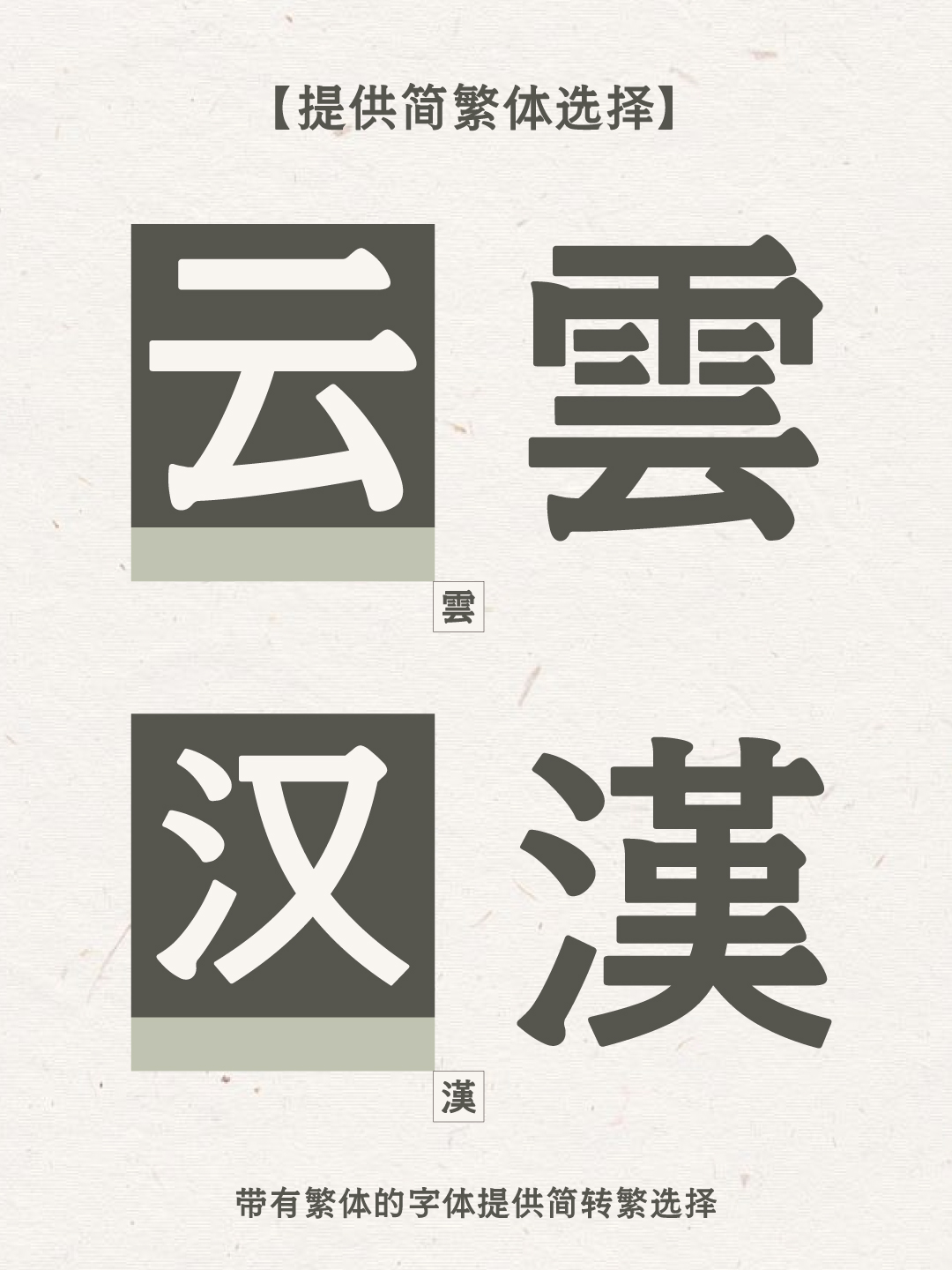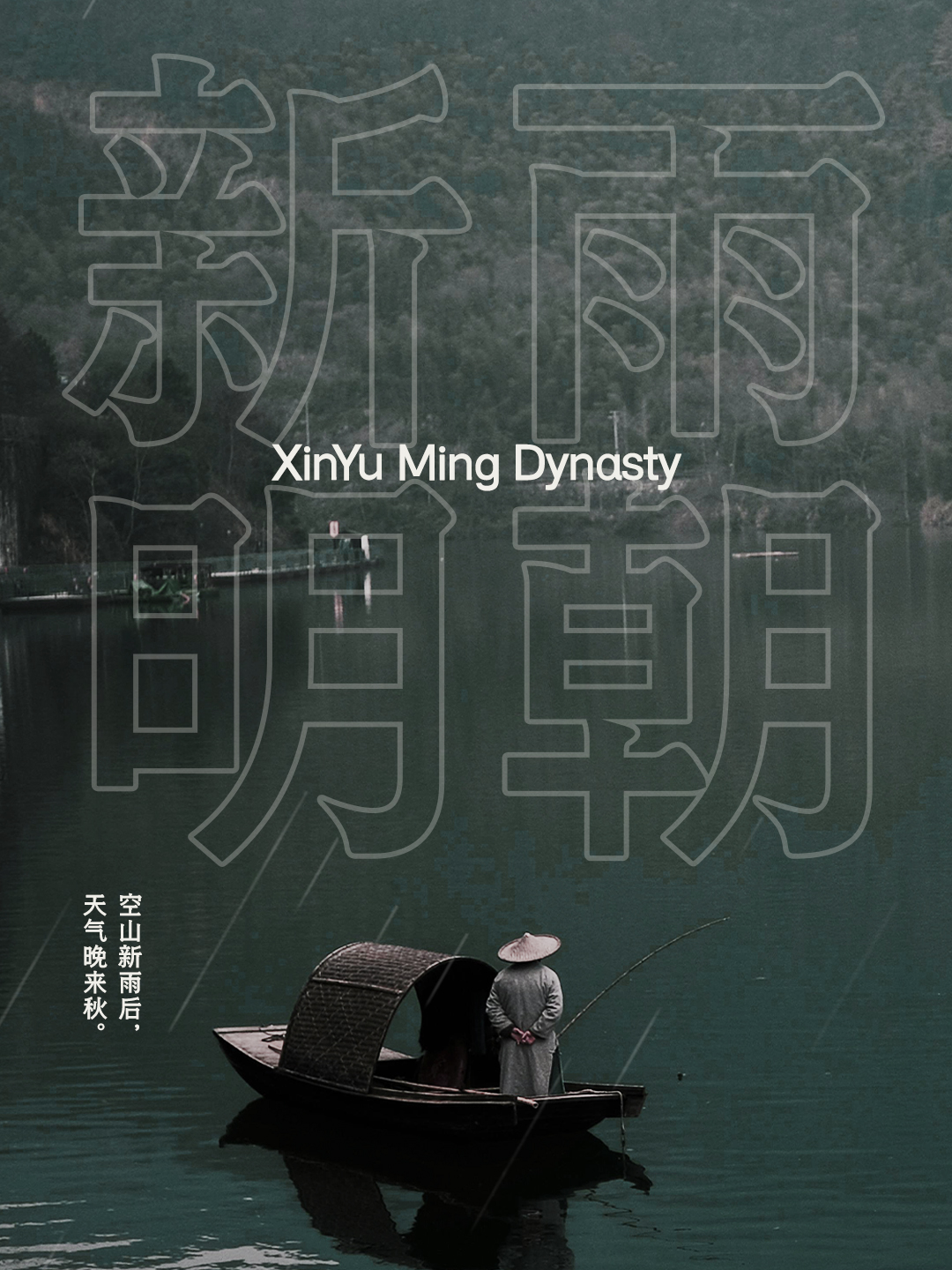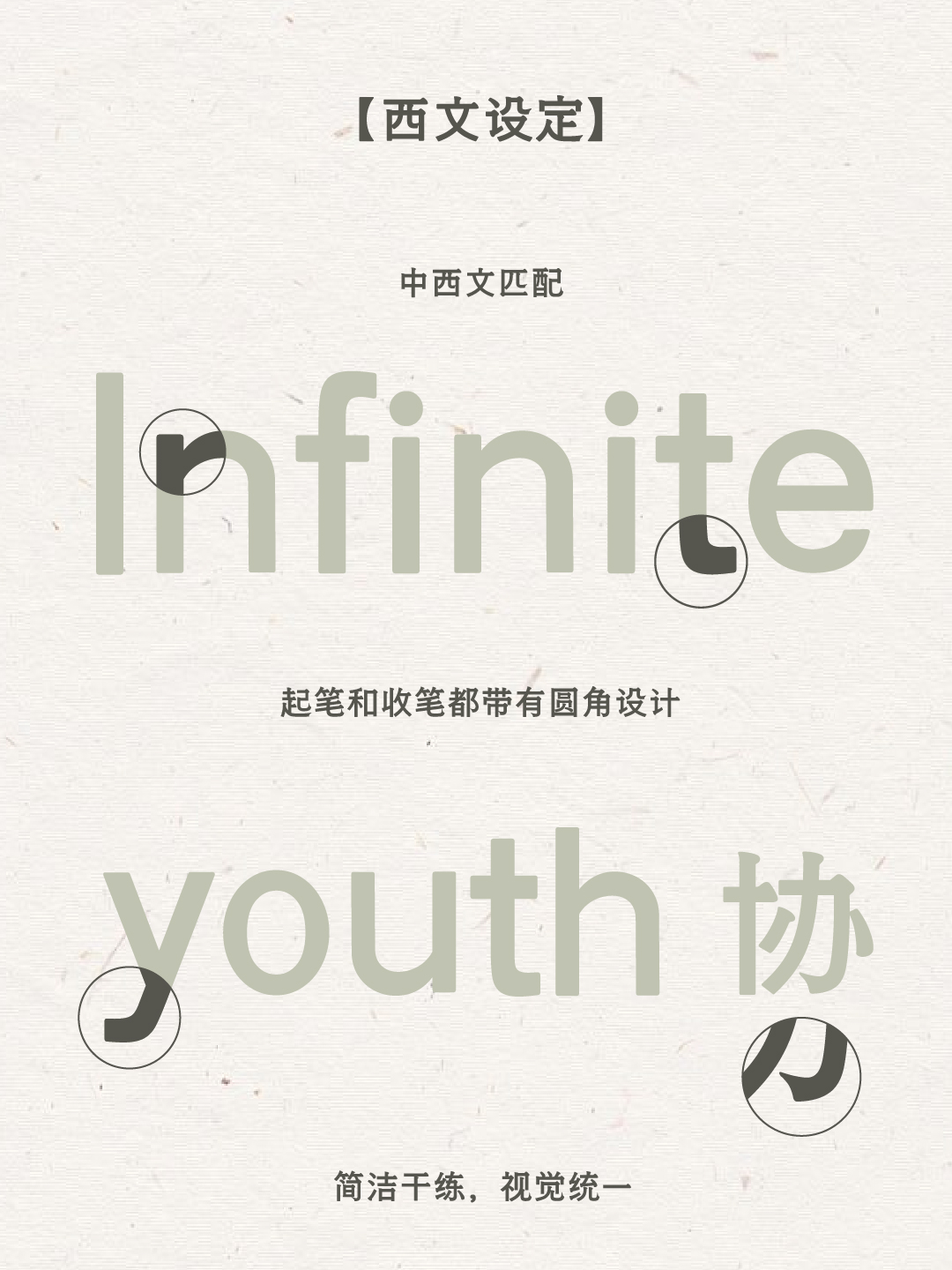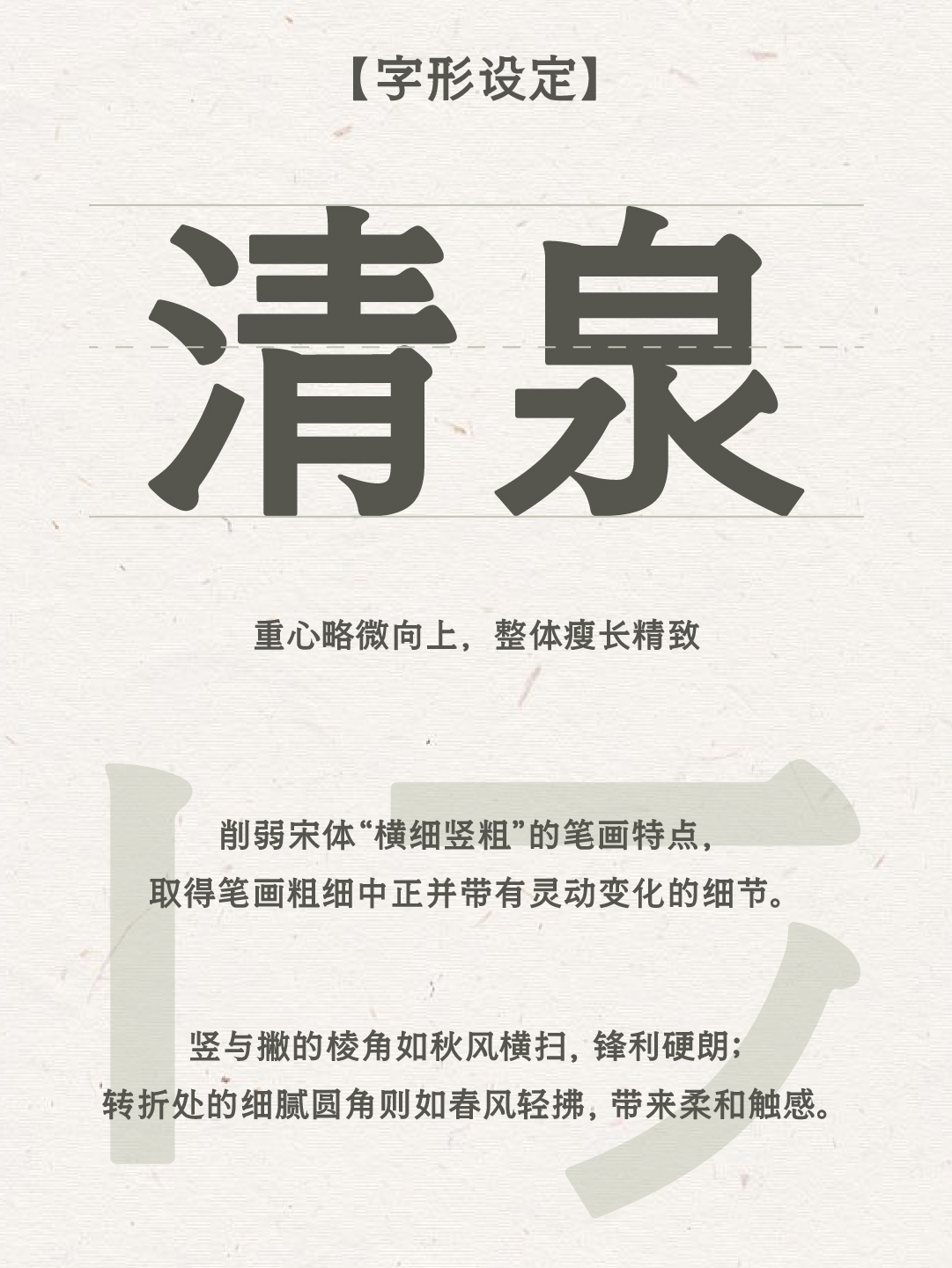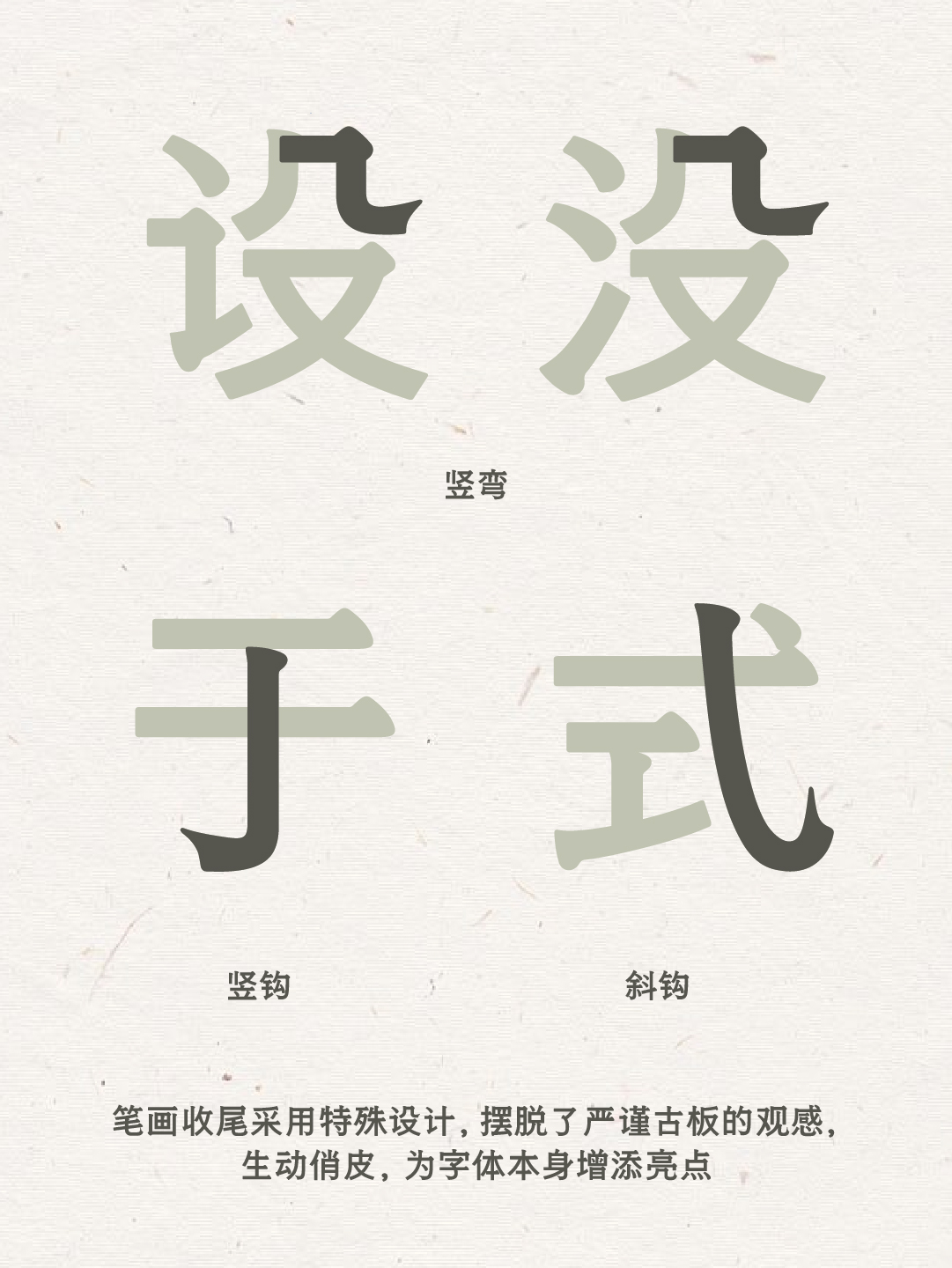
【字体创意溯源】
“空山新雨后,天气晚来秋”,王维笔下《山居秋暝》里的“新雨”意境,宛如一幅清新隽永的画卷,在眼前徐徐展开。雨过天晴,世间万物仿佛被赋予了新的生命,焕发出勃勃生机,而雨本身,也象征着事物在时光流转中的蜕变与新生。这套「新雨明朝体」字体,恰似从这诗意的意境中汲取灵感,在传承宋体端正、优雅风姿的同时,巧妙融入黑体的锐利与力量感,二者相互交融、平衡共进,这正是「也字工厂」制字理念的生动诠释——温柔中蕴含锋芒,于传统里拥抱创新,书写着字体设计的独特篇章。
【字体独特魅力】
「新雨明朝体」是「也字工厂」专业团队耗时一年精心雕琢的精品字体,它实现了简繁扩展,能够满足不同场景的使用需求。
宋体与黑体的完美融合:它既保留了宋体的端庄典雅,又融入了黑体的锐利刚劲,达成古典与现代的精妙平衡。相较于传统宋体,它多了一份硬朗与果敢;相较于黑体,又增添了几分优雅与温婉,在字体的世界里独树一帜。
笔画刚柔并济的艺术:仔细观察其笔画,竖与撇的棱角犹如秋日里飘落的树叶,边缘锋利,展现出一种坚韧不拔的个性;而转折处的细腻圆角处理,又仿佛春风轻拂脸颊,给人以温柔细腻的触感,刚与柔在这里达到了和谐的统一。
灵动细节的巧妙点缀:在“钩”的细节处理上,设计师更是独具匠心,让整个字体看起来更加生动灵活,仿佛每一个笔画都蕴含着生命的律动,为字体增添了一份独特的魅力。
【应用多元场景】
「新雨明朝体」独特的字形设定,决定了它是一款面向内文使用的优质字体,尤其适合作为小标题和正文,能够为文字内容增添一份别样的韵味。
其刚柔并济的独特气质,使得它在茶饮、食品、美妆、酒店民宿等旨在展现新中式温度的产品设计中,能够大放异彩。在这些领域,它既能传达出传统文化的深厚底蕴,又能展现出现代设计的时尚感,为产品赋予独特的魅力。
此外,由于它融合了宋体的易读性以及黑体的远视距效果,无论是在纸质印刷品上,还是在电子显示设备中,都有着出色的表现。其醒目的视觉效果和清晰的辨识度,能够确保信息准确无误地传达给读者,成为各种媒介上的理想选择。